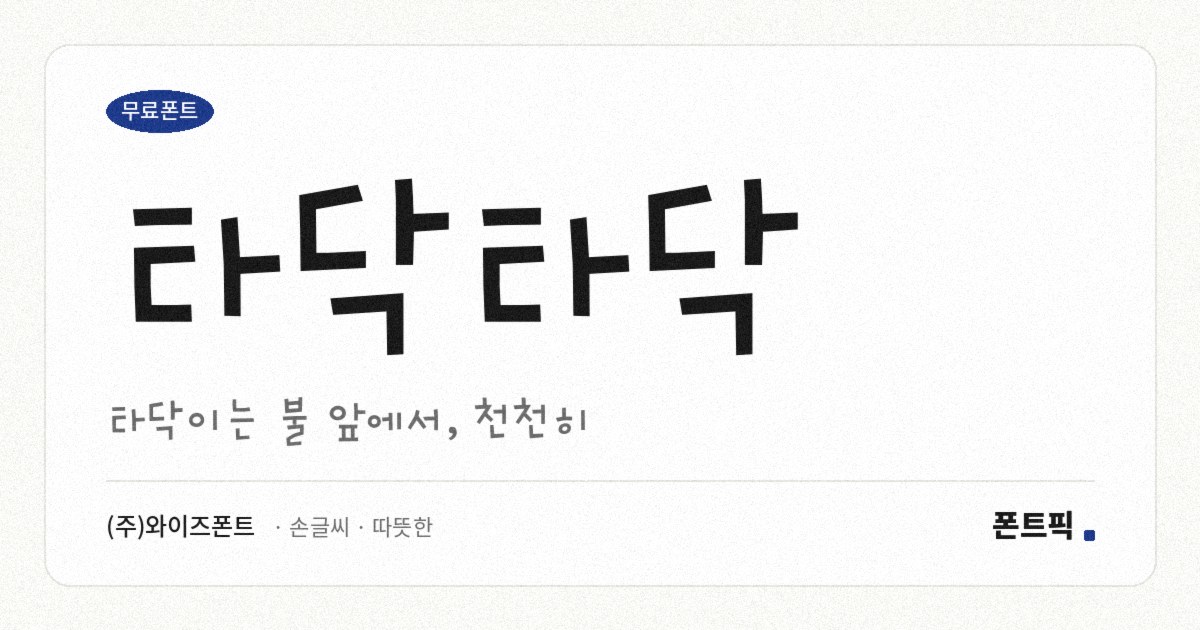
타닥타닥 서체 견본
타닥타닥
TDTDTadakTadak
타닥타닥 소개
폰트 구독 서비스 타닥타닥을 운영하는 와이즈폰트가 만든 손글씨 서체입니다. 제작 배경이나 조형 의도를 밝힌 공개 자료는 찾지 못했습니다. 그래서 아래는 폰트 파일을 직접 조판하고 재어 본 내용입니다.
가장 눈에 띄는 성질은 네모틀을 벗어난 구조입니다. 받침이 없는 글자와 있는 글자의 높이 차이가 0.34em으로, 폰트픽에 올라온 한글 서체 가운데 세 손가락 안에 듭니다. 받침이 붙으면 글자가 아래로 쭉 내려가고 없으면 납작하게 눌리기 때문에, 글줄이 자로 잰 듯 맞아떨어지지 않고 손으로 쓴 것처럼 오르내립니다. 낱자는 높이보다 폭이 1.5배 가까이 넓어 가로로 퍼진 인상이고, 가로획과 세로획의 굵기가 거의 같아 펜으로 한 번에 그은 듯한 느낌을 냅니다.
현대 한글 11,172자를 모두 담고 있어 어떤 글자를 넣어도 빠지지 않습니다. 굵기는 하나뿐이라 제목과 본문을 굵기로 나눌 수 없고, 획이 고르고 가는 편이라 작게 쓰면 인상이 흐려집니다. 카드 뉴스 제목이나 짧은 감성 문구처럼 크게 한두 줄 쓰는 자리에 어울립니다.